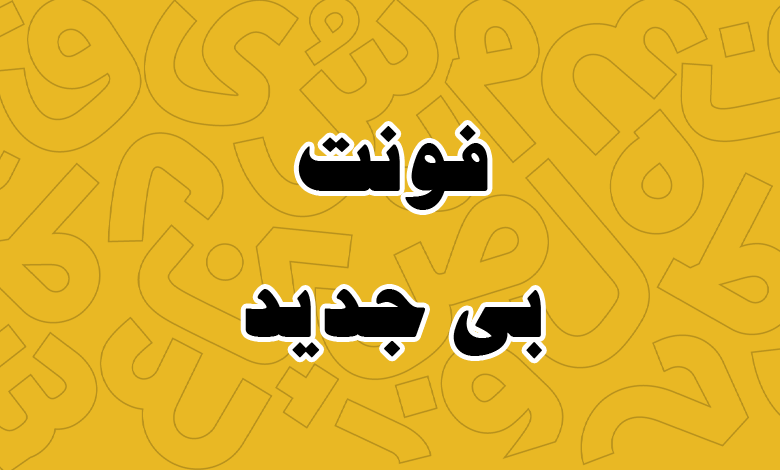
فونت بی جدید (B Jadid)
فونت بی جدید (به انگلیسی: B Jadid) قلمی به سبک خط نسخ است که با وزن بولد طراحی شده و میتوانید از آن در عناوین و تبلیغات استفاده کنید. در ادامه میتوانید به لینک دانلود رایگان فونت بی جدید دسترسی داشته و این قلم را در فرمتهای مختلف دریافت کنید.
فونت فارسی بی جدید توسط شرکت برنا رایانه در دهه ۷۰ طراحی شده است و پس از چند آپدیت، آخرین نسخه آن در سال ۷۹ با شماره نسخه ۲.۰۱ در دسترس قرار گرفته که میتوانید برای زبان فارسی از این فونت استفاده کنید.
فونت بی جدید فارسی است که با وزن بولد ارائه شده است. فونتهایی با وزن بولد اصولا برای استفاده در متون کوتاه مناسب هستند و توصیه نمیشود که برای متون طولانی از آنها استفاده کنید.
پیشنمایش و امکانات فونت بی جدید (B Jadid)
حروف این فونت ضخیم نسخ، برای استفاده در حوزههای مختلفی همچون تبلیغات، فونت عنوان کتاب و مجلات، فونت بیلبوردهای تبلیغاتی، فونت مطبوعات و حتی فونت تامنیل برای ویدئو و پست در شبکههای اجتماعی مناسب هستند.
این فونت دارای ضخامتی است که بهخوبی خوانده شده و ظاهری چاق به فونت داده است. زمانی که از این فونت در عناوین استفاده کنید، هرچه ابعاد نوشته بزرگتر باشد فونت ساختار نمایشیتر داشته و خود را بهتر نشان خواهد داد. بهویژه در بخش نقاط که به صورت ناپیوسته و لوزیشکل طراحی شدهاند.
در طراحی این فونت چشمیها ساختاری ریز دارند و دندانه حروفی مثل «س، ش» ریز و جزئی کار شده است. بخش افقی حروف که در خط کرسی قرار دارند بیشترین ضخامت را بهخود اختصاص دادهاند و در مقابل سایر بخشها ضخامتی کمتر دارند. چنین سبک فونتی را پیش از این در قلمهایی نظیر فونت ملی یا فونت جدید ونوو مشاهده کردهایم.
فونت بی جدید TTF که میتوانید در انواع نرمافزار مانند ورد، پاورپوینت، اینشات و کپ کات از آن استفاده کنید متون فارسی را مشابه تصویر بالا به نمایش خواهد گذاشت. همانطور که در تصویر نیز مشهود است، این فونت کاملا فارسی بوده و از گلیفهای سایر زبانهای عربی یا لاتین پشتیبانی نمیکند.
اما با توجه به رسم خط یکسان، میتوانید از این قلم در زبان عربی برای کلماتی که دارای گلیف یکسان هستند استفاده کنید. با این تفاوت که برخی حروف عربی مثل «ک، ؤ، ئ» و اعداد «۴۵۶» پشتیبانی نمیشود. برای کاراکترهای خاص مثل نمونهای که در تصویر میبینید نیز همینطور است.